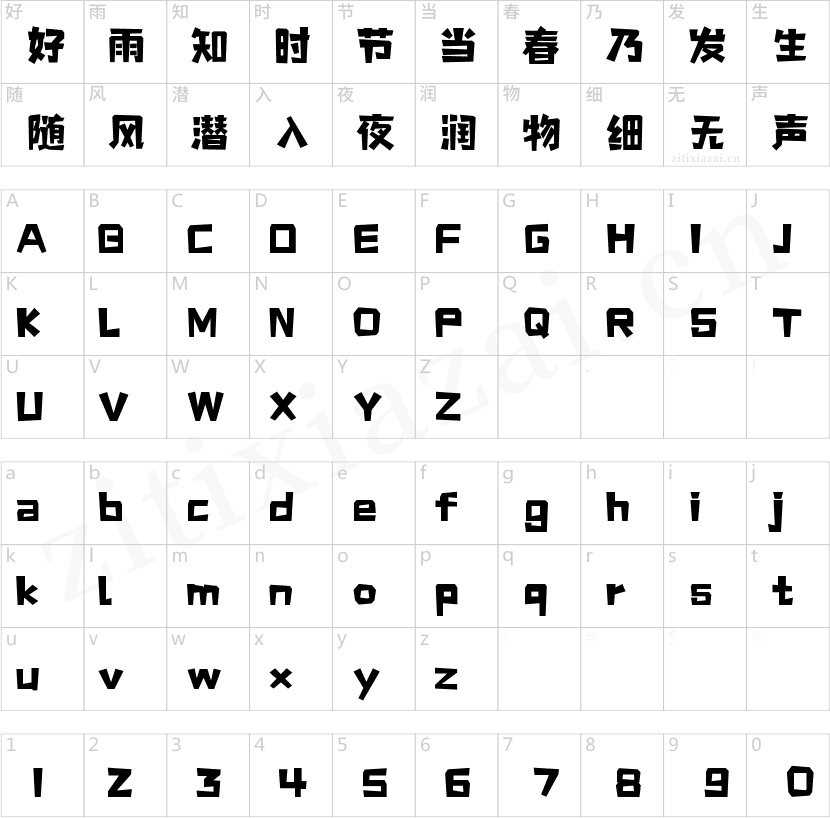
字小魂星光闪闪体
字小魂星光闪闪体,这款字体结构工整、笔画清晰,兼顾美观与易读性,适用于标题、正文、海报、包装、LOGO 等多种场景。字形优雅稳定,风格百搭耐看,适配日常排版与创意设计,让文字呈现更舒适、更具质感。字小魂星光闪闪体一笔一画,皆是细节,以均衡的比例、流畅的线条打造舒适视觉体验,字形端正大气,风格简约现代。无论是商业设计、品牌宣传还是日常排版,都能轻松驾驭,让文字更有格调与力量。字小魂星光闪闪体字体下载。
字魂字体字小魂星光闪闪体字体是由字魂创意字库设计并生产的一款可商用的字体,被收录于字小魂系列。该字体支持GB-2312标准,包含6763个中文、字母、符号和数字,字体类型偏向卡通可爱,具有活泼、动漫、可爱的风格,在市面上广泛用于化妆美容、包装印刷、旅游等场景。